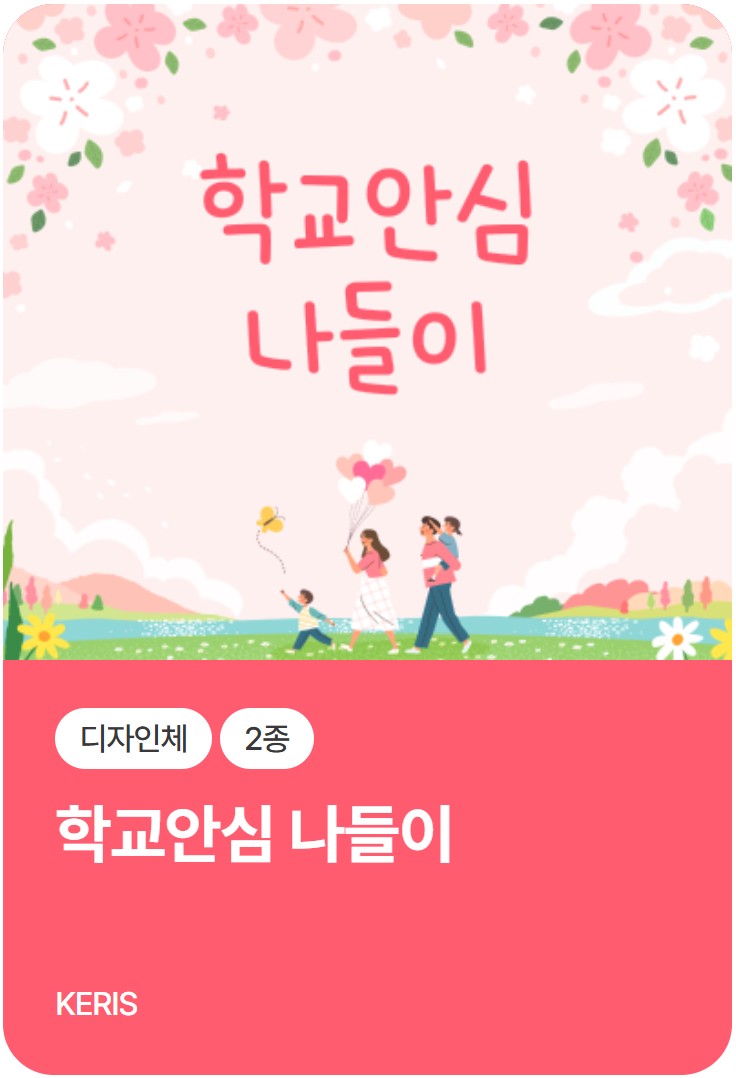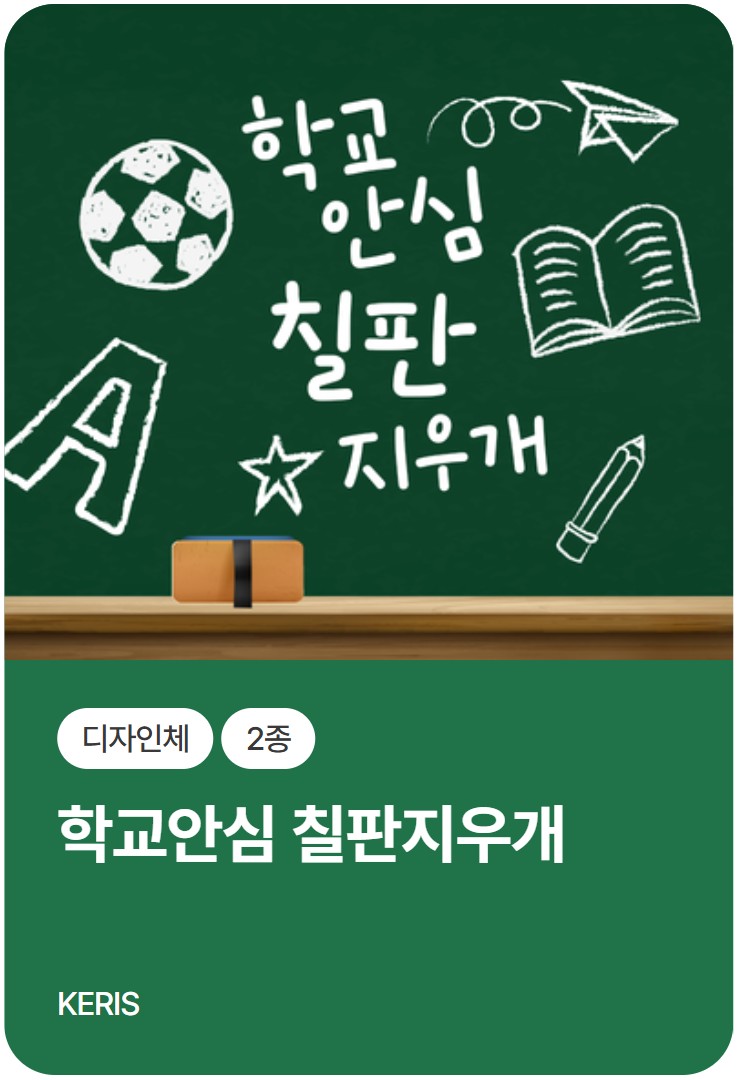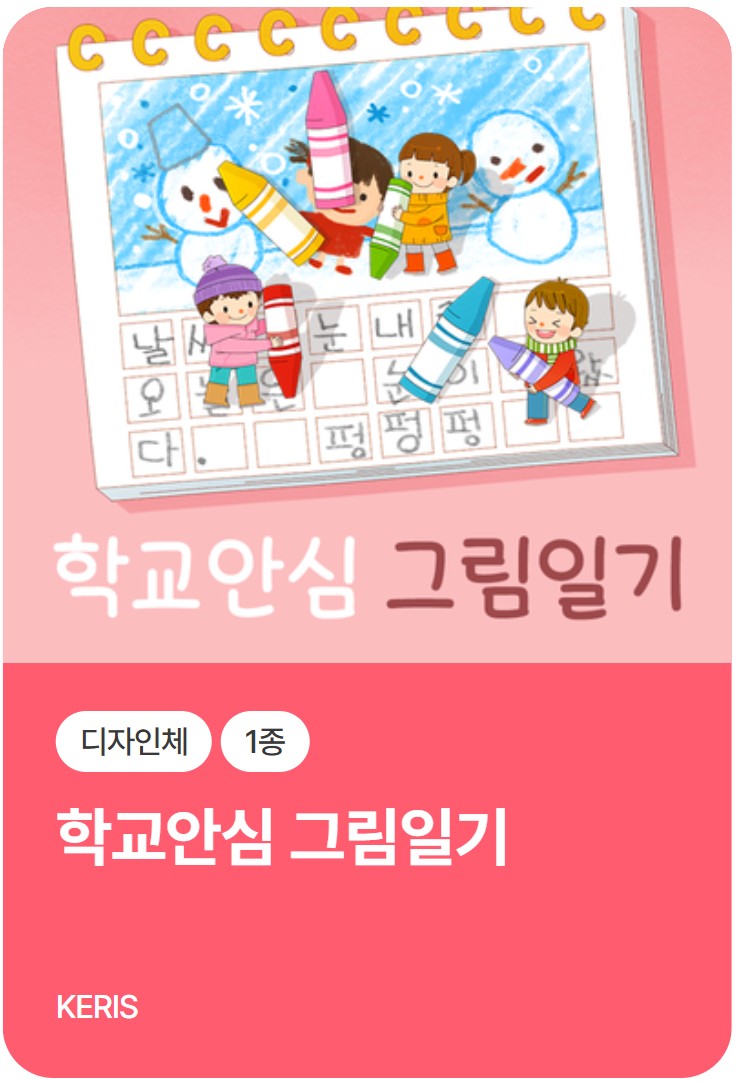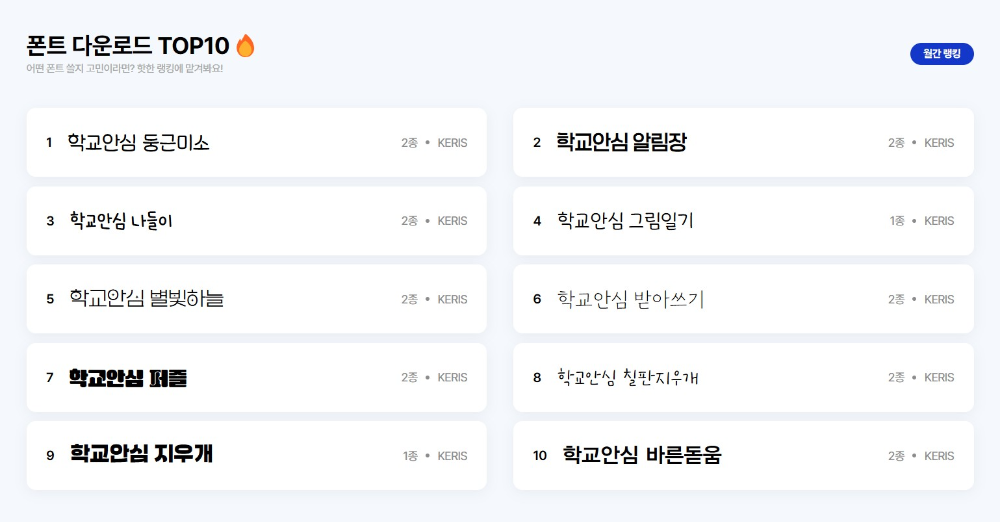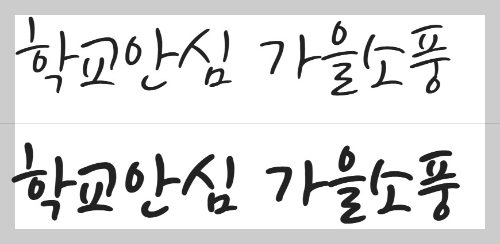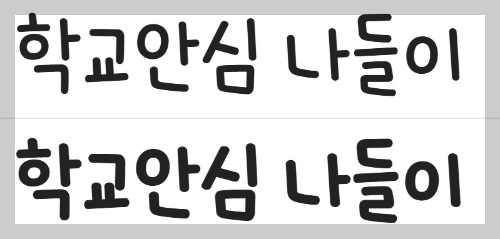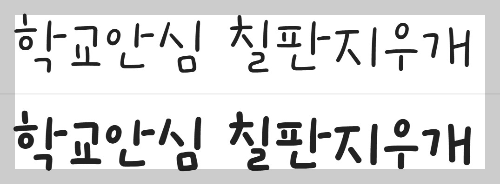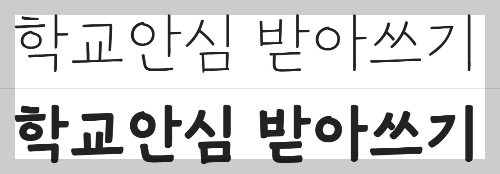
상업적 사용이 가능한 무료 한글 글꼴을 찾고 계신가요? 교육 현장과 공공기관, 개인 블로그 등에서도 안심하고 사용할 수 있는 글꼴이 있습니다. 바로 한국교육학술정보원(KERIS)에서 제공하는 ‘학교안심폰트’입니다. 본 글에서는 학교안심폰트의 개요, 글꼴 종류, 라이선스 정보와 다운로드 방법까지 자세히 알려드립니다.
학교안심폰트란 무엇인가요?
‘학교안심폰트’는 교육부와 한국교육학술정보원(KERIS)이 전국 초·중·고등학교 및 교육기관을 위해 제작한 무료 글꼴입니다. 이 폰트는 누구나 자유롭게 사용할 수 있도록 제공되며, 특히 상업적 이용까지 가능해 다양한 콘텐츠 제작에 매우 유용합니다.
이 폰트는 글꼴 저작권 문제로부터 교사와 학생, 교육기관을 보호하고, 안전한 교육 콘텐츠 환경을 조성하기 위한 목적에서 개발되었습니다. ‘학교안심폰트’라는 이름처럼 라이선스 걱정 없이 안심하고 사용할 수 있다는 점이 가장 큰 장점입니다.
제공되는 글꼴 종류와 특징
KERIS 학교안심폰트는 300종이 넘는 글꼴로 구성되어 있으며, 각각의 글꼴은 초등·중등 교과서 필체 또는 친숙한 인쇄체 스타일을 기반으로 제작되었습니다. 글꼴은 각각 명확한 사용처와 감성을 담고 있어 다양한 디자인 작업에 유용하게 활용할 수 있습니다.
손글씨 서체 8종 추천